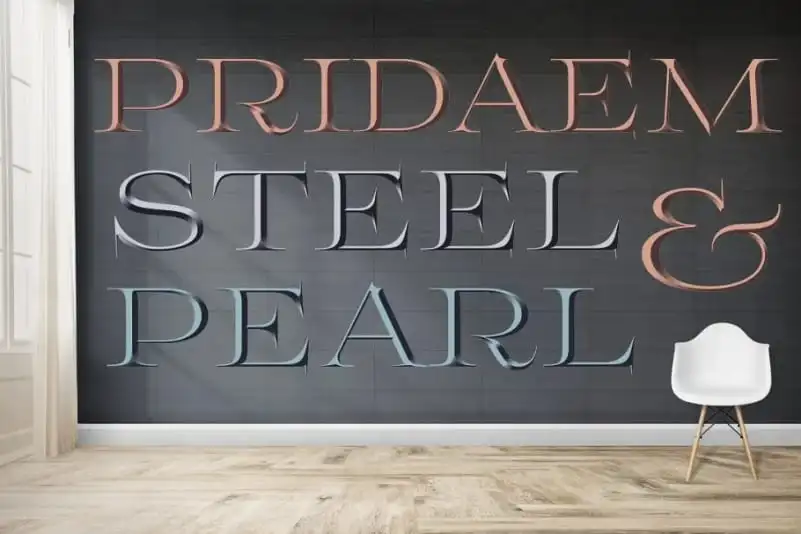
PridaEm Cooper Serif Font – Download Grátis
PridaEm Cooper Serif é uma fonte séria projetada pela glukfonts inspirada nas brilhantes matizes metálicas. Inspirado no metal com seu aço inox, alúmina, cobre, ouro e pedra preciosa, essa fonte oferece uma paleta vibrante que se adapta perfeitamente para qualquer aplicação visual. Suas letras em formato vectorial permitem criar cabeçalos, banners e slogans de anúncios a qualquer tamanho. Além disso, o OpenTypeSVG .TTF e WOFF formatos permitem personalizar ainda mais suas obras finais. Como uma fonte colorida para se enriquecer com estilos decorativos, PridaEm Cooper Serif é perfeita para ambientes que valorizam tanto a modernidade quanto o brilho.